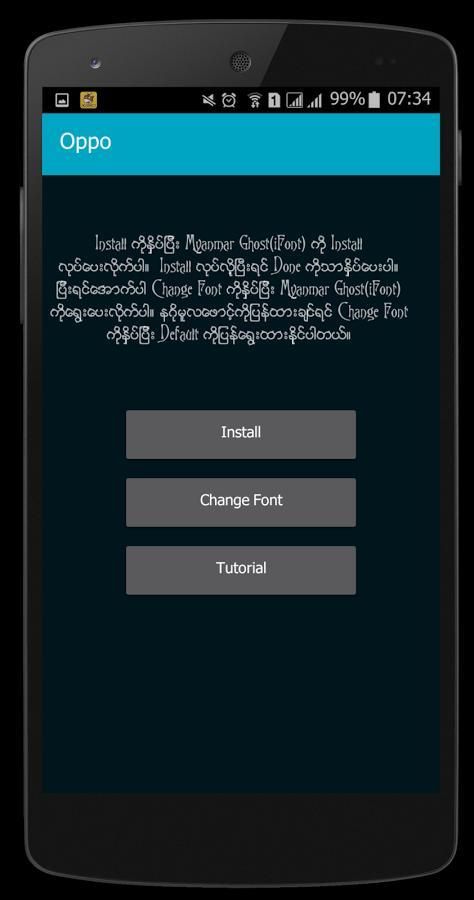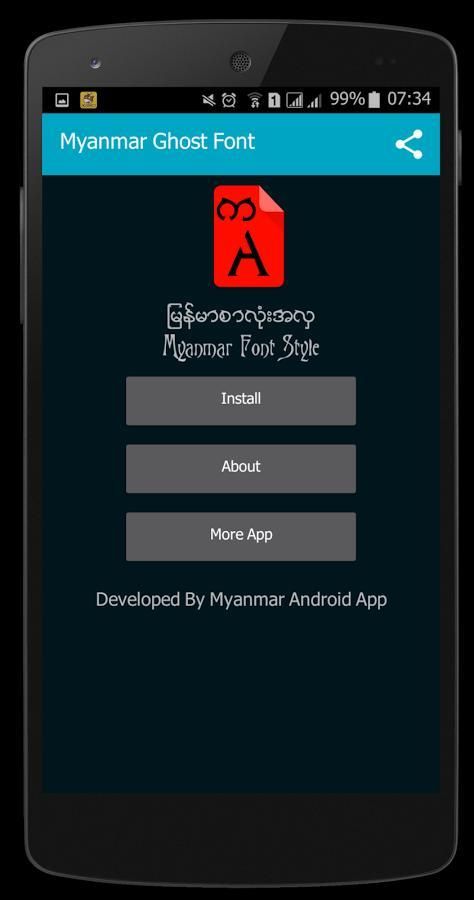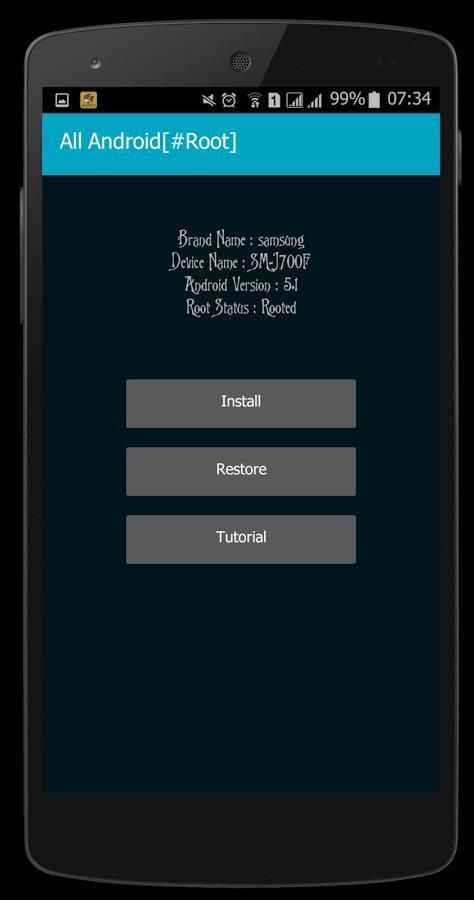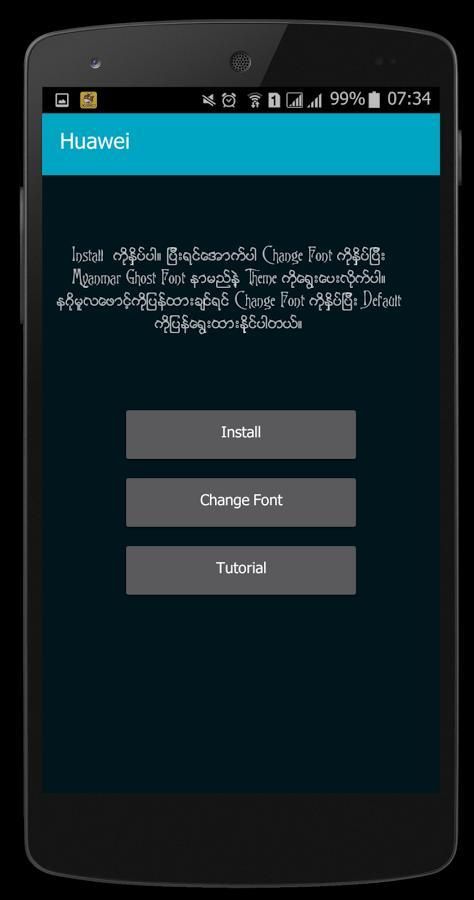
"Myanmar Ghost" Font is Beautiful Myanmar Zawgyi Font Style!
ဖုန္းမွာျမန္မာစာလုံးအလွသုံးခ်င္သူမ်ားအတြက္
Myanmar Ghost ဆိုတဲ့စာလုံးပုံစံအသစ္ေလးပါ။
အရမ္းလန္းပါတဲ့စာလုံးပုံစံေလးပါ။